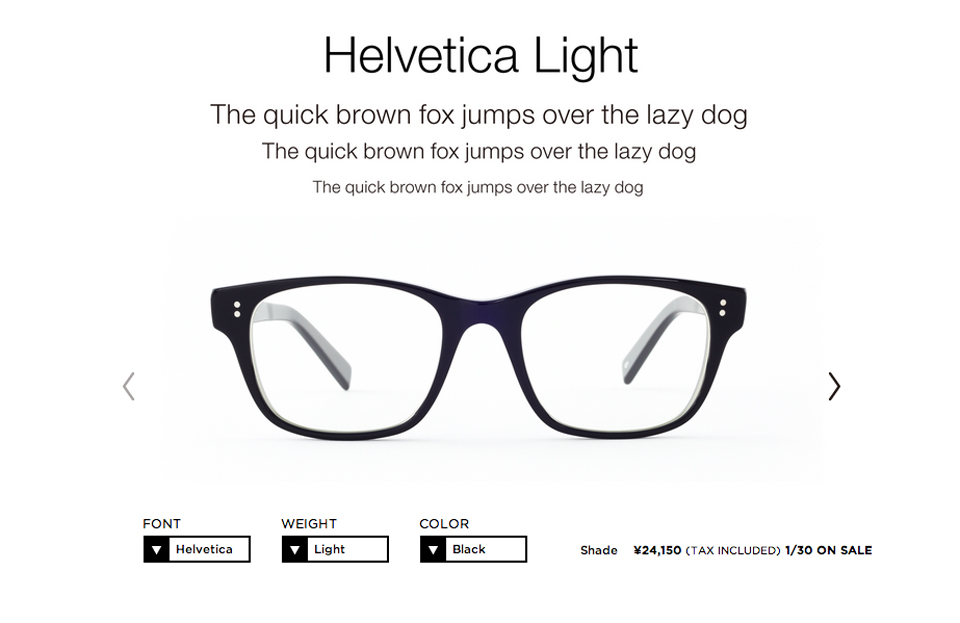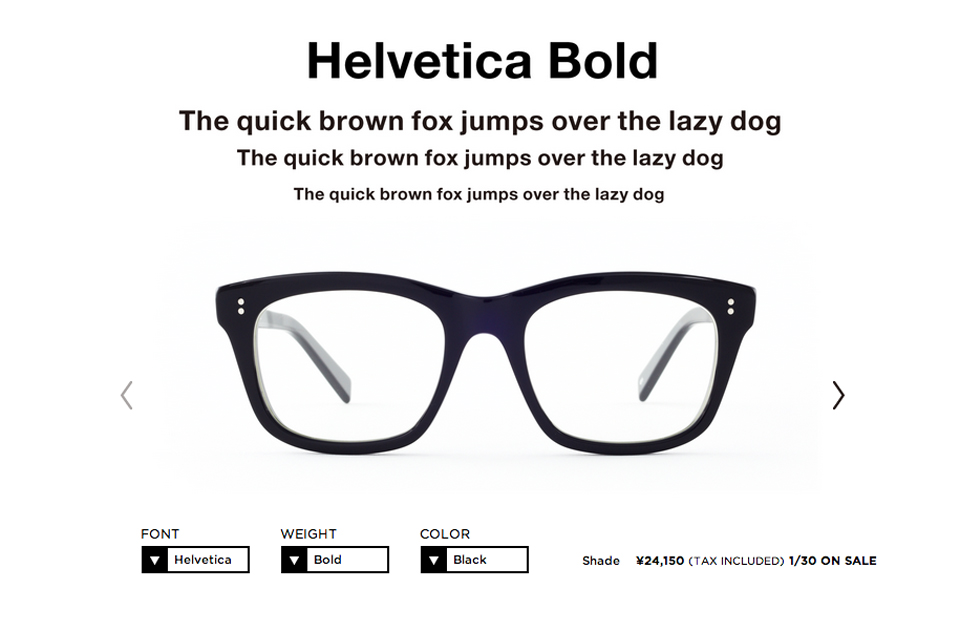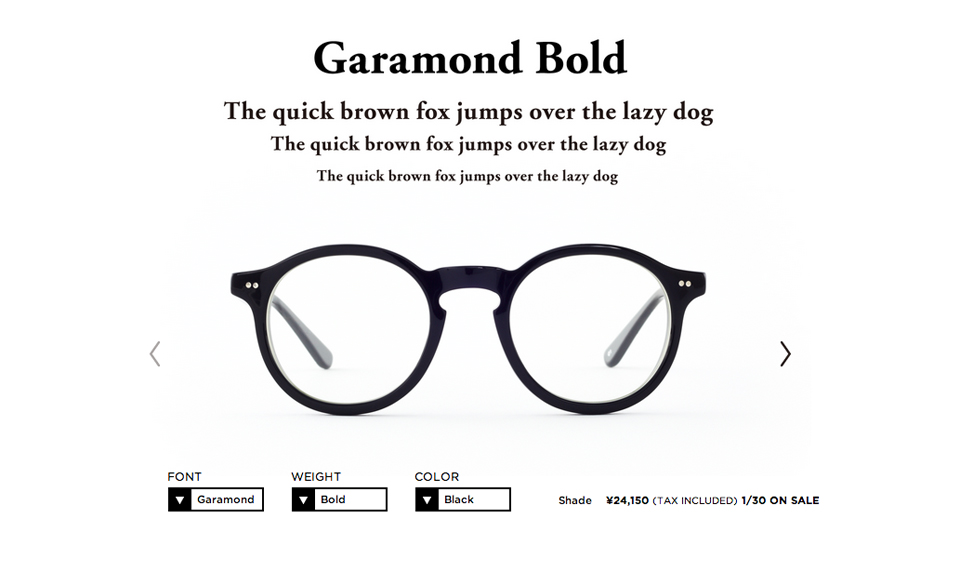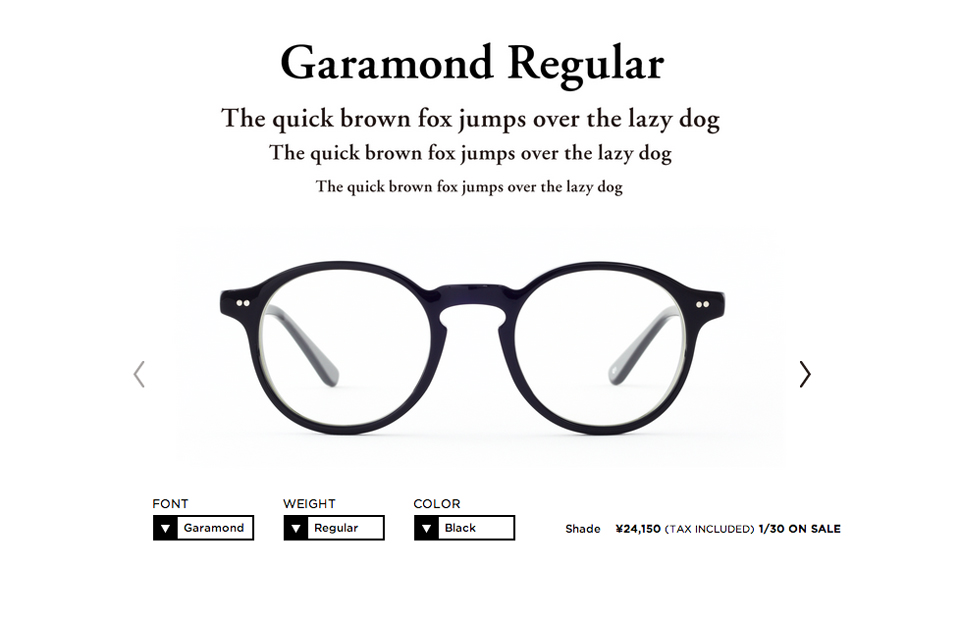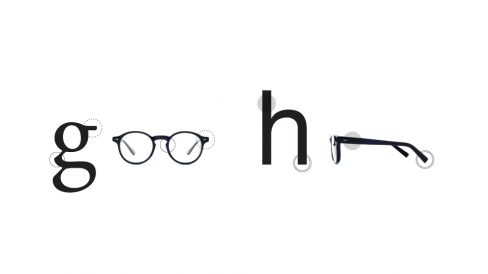
Óculos inspirados em tipografia
Empresa japonesa cria modelos de óculos baseados no design das fontes Helvetia e Garamond
A empresa japonesa Type quer que você use óculos cujo design foi totalmente inspirado em tipografia.
Para começar, foram cridas duas linhas de óculos, cada uma baseada nas fontes Helvetia e Garamond, aprofundando modelos a partir de suas variações.
Cada linha possui três versões de óculos – light, regular e bold – que delineiam a espessura das armações. Além disso, todos os produtos estão disponíveis em preto, transparente (“clear”) e estampado (“tortoise”).
A empresa faz um bom trabalho ao extrair as principais características de cada fonte, e usá-las para personificar seus produtos.
Enquanto a linha Helvetica tem um design mais comum ao retratar as características que tornam a fonte tão popular e compatível com diversas funções e necessidades, a linha Garamond segue uma abordagem mais diferenciada e busca destacar seus diferenciais, resultando em um design de curvas que une ousadia e vintage ao mesmo tempo.